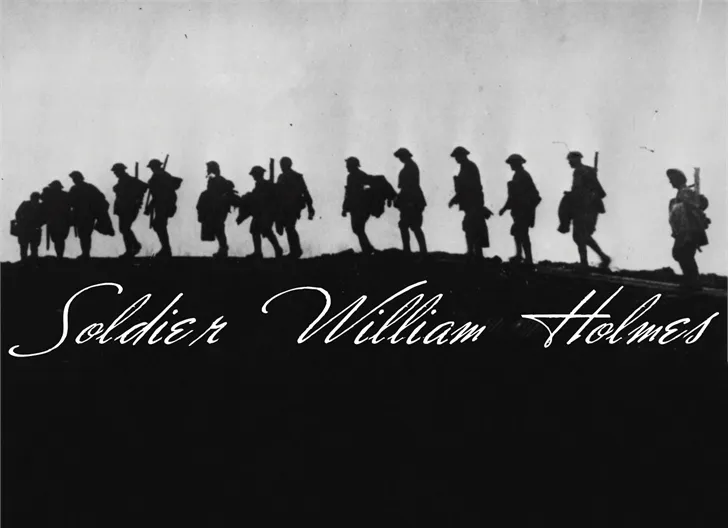
Soldier William Holmes Font – Fonte Grátis
Soldier William Holmes Font
Esta fonte ‘Soldier William Holmes’ é uma oferta gratuita para uso pessoal e não comercial, uma característica que certamente a torna valiosa para designers amadores e iniciantes. No entanto, os criadores do Intellecta Design valorizam profundamente o seu trabalho histórico sobre as letras, a escrita por conta própria e tipografia, por isso oferecem a possibilidade de fazer doações. A fonte ‘Soldier William Holmes’ é um documento handwritten que oferece uma variedade única de formas e estilos, adequada para projetos de design gráfico ou criação de material educativo. Com sua capacidade única de reproduzir o estilo autêntico da escrita, esta fonte irá trazer aos seus trabalhos um toque único de personalidade histórica.